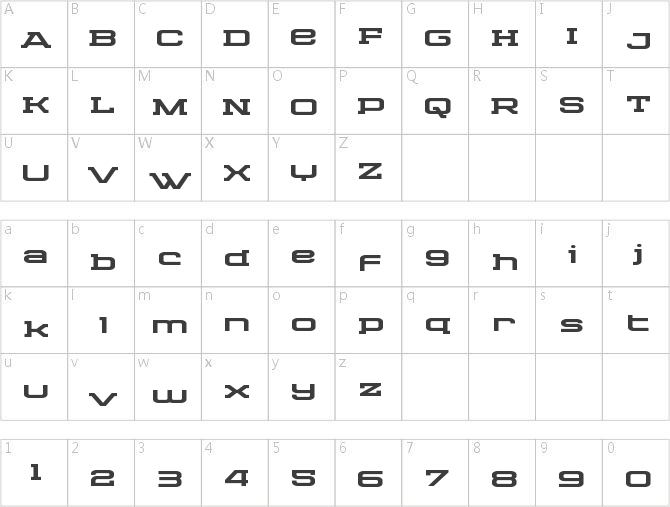
字體名稱: cydonia
cydoniacenturyexpand
cydoniacenturyexpand字體字庫是一款讓人賞心悅目、百看不厭的英文字體,適合各類廣告和產(chǎn)品包裝設(shè)計應(yīng)用,字體大小0.03MB,格式為ttf字體,上傳用戶是13226568769,作者/版權(quán)方為未知